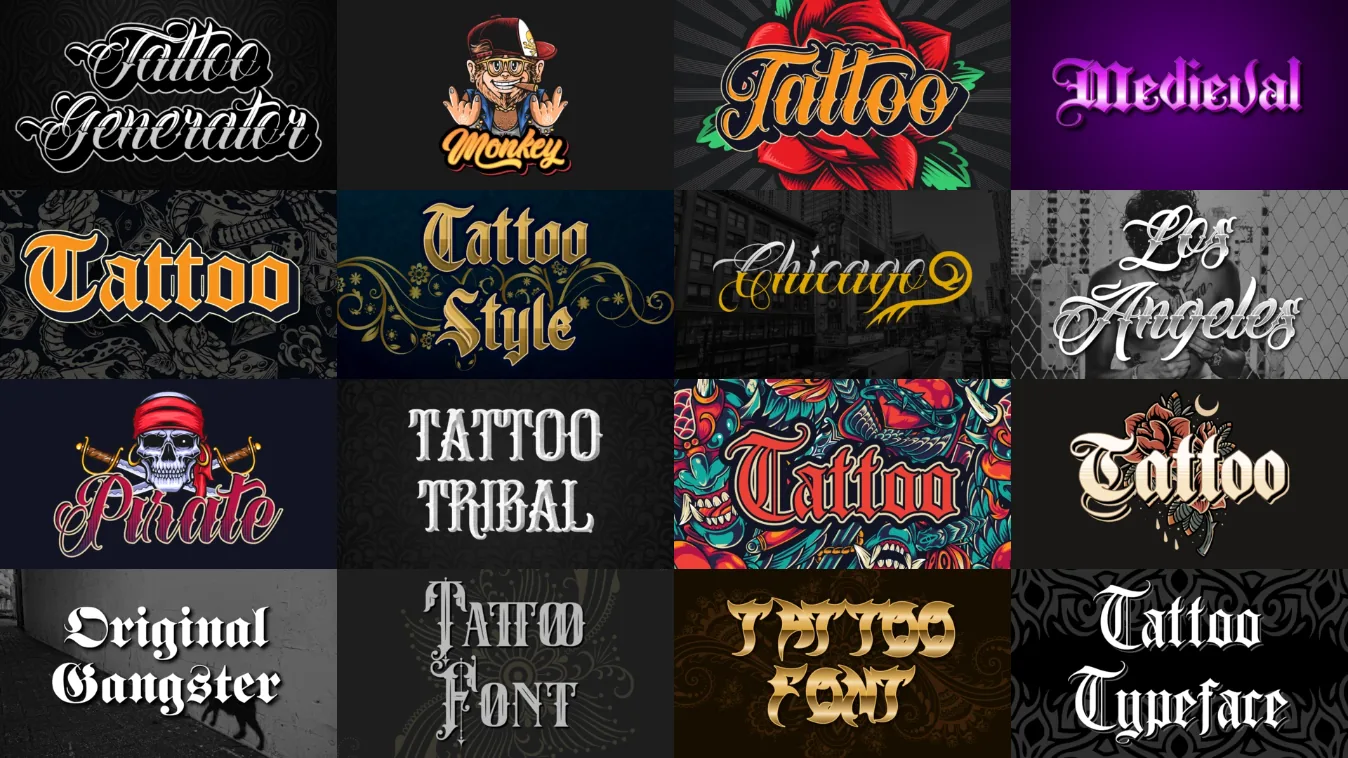
Ciao a tutti, anime creative! Non vediamo l'ora di condividere una notizia fantastica: il nostro sito è appena diventato molto più figo grazie all'arrivo del nostro nuovissimo Generatore di font per tatuaggi online! Questo strumento geniale è qui per aggiungere un pizzico di creatività ai tuoi progetti digitali, soprattutto se hai sempre sognato di avere testi in stile tatuaggio che urlano "sei proprio tu" in ogni pixel.
In un mondo dominato da emoji e GIF, esprimere la propria unicità è più importante che mai. Il nostro generatore di font online attinge al fascino senza tempo dei tatuaggi, offrendoti la possibilità di creare testi audaci, unici ed espressivi proprio come te.
- Festa di font: Tuffati in una vera festa di font! Abbiamo un vero e proprio buffet di stili ispirati sia all'arte del tatuaggio classica che a quella contemporanea. Scegli tra eleganti caratteri corsivi, lettering funky o qualcosa di completamente fuori dagli schemi: la scelta è tutta tua.
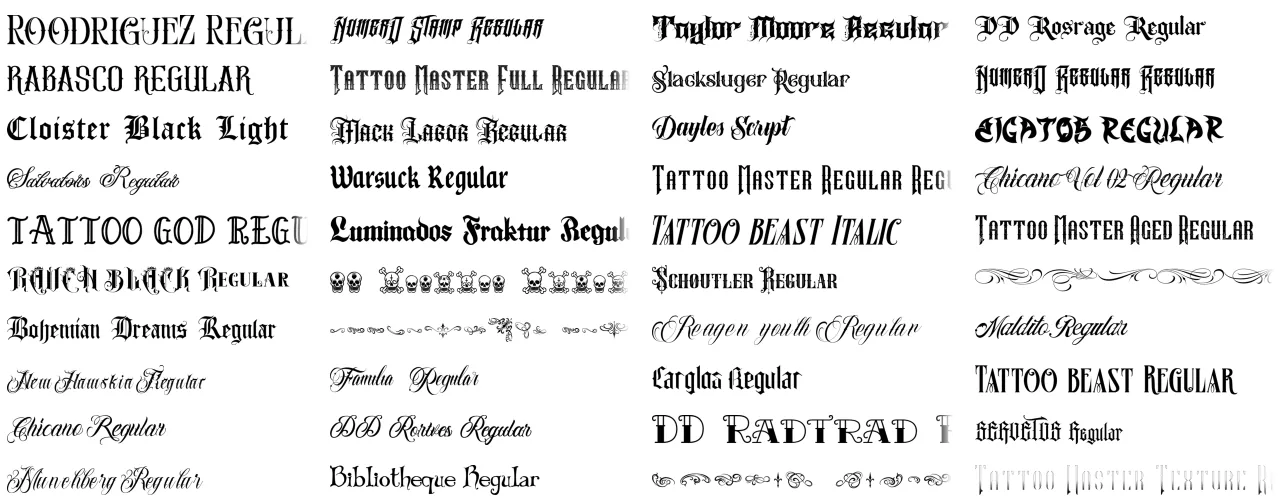
- Magia della personalizzazione: Rendi il tuo testo davvero tuo con un tocco di magia nella personalizzazione. Regola dimensione, spaziatura e aggiungi persino qualche curva per ottenere quel perfetto stile tatuaggio. E perché non sperimentare con i colori fino a trovare quello che ti fa battere il cuore?
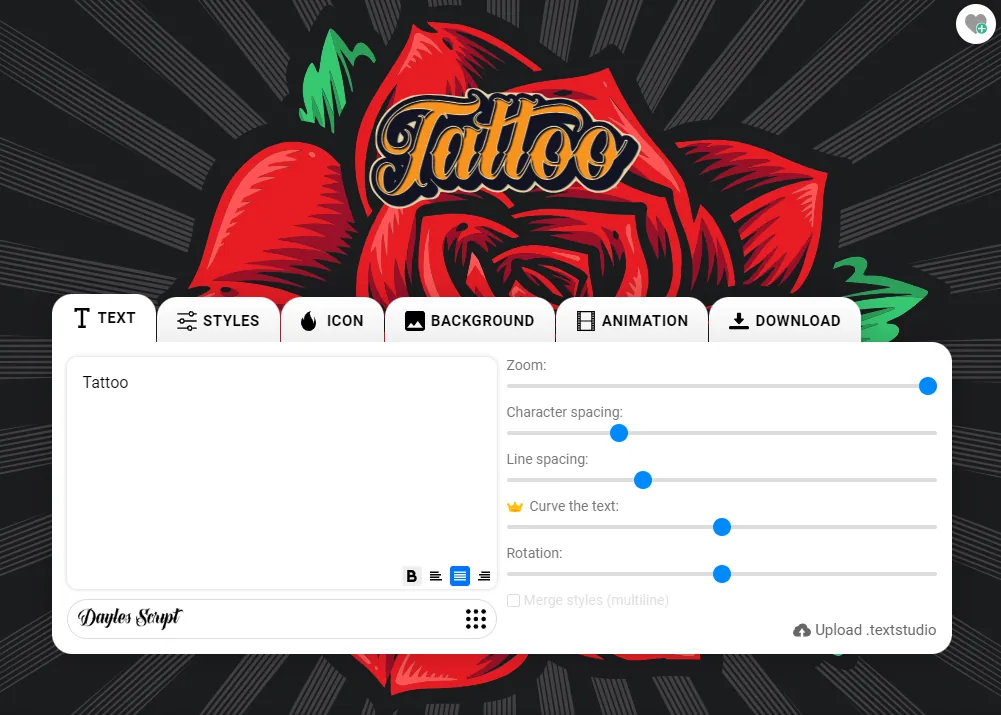
- Anteprima in festa: Ti chiedi come apparirà la tua creazione? Non dire altro! La nostra funzione di anteprima ti permette di dare una sbirciatina prima di decidere. È come avere il tuo tatuatore personale, ma nel mondo digitale.
- Semplicità straordinaria: Che tu sia un mago della tecnologia o che ti stia solo avvicinando al mondo creativo, la nostra interfaccia intuitiva è pensata proprio per te. Lascia correre la fantasia senza alcun grattacapo tecnico.
- Scegli il tuo gusto: Esplora il paese delle meraviglie dei font e scegli quello che rispecchia il tuo stile. Vuoi qualcosa di classico? Ce l'abbiamo. Ti senti un po' funky? Abbiamo anche quello.
- Dagli un tocco in più: Personalizza a piacimento. Regola la dimensione, ritocca la spaziatura, aggiungi un po' di colore: questo è il tuo momento per brillare!
Allora, cosa aspetti? Tuffati nel nostro Generatore di font online, dai voce all'artista che è in te e lascia correre la creatività. Che tu stia sognando un tatuaggio virtuale o voglia semplicemente ravvivare la tua vita digitale, questo strumento è il tuo biglietto per un mondo di divertimento creativo e amichevole. Facciamoci tatuare, in digitale, ovviamente! 🎨✨